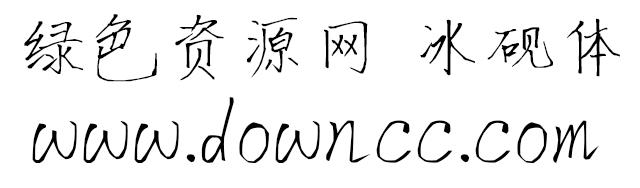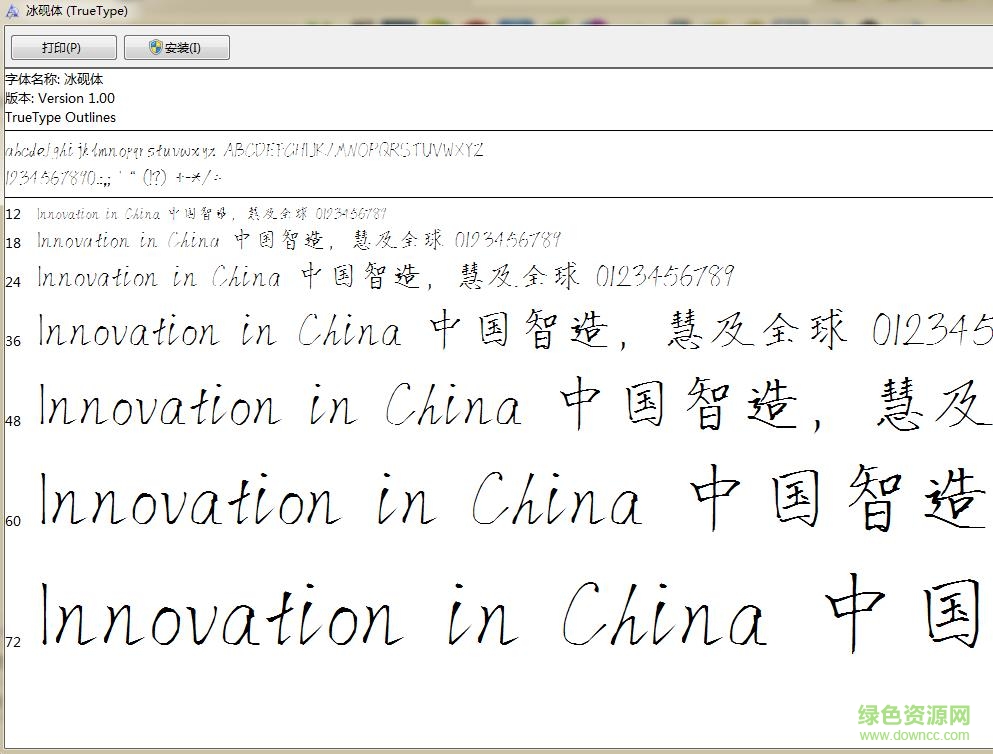
冰硯體ttf字體的每一個(gè)都感覺像是結(jié)冰一樣的效果,讓用戶們?cè)谑褂玫臅r(shí)候能夠感受到冰天雪地一般的體驗(yàn),這款自己在眾多行業(yè)都能夠帶來最佳的字體效果!
這款字體的獨(dú)特之處在于字里行間的行文風(fēng)格十分美麗,每一個(gè)落筆處都有一處如結(jié)冰般的凝固字體效果,十分好看!